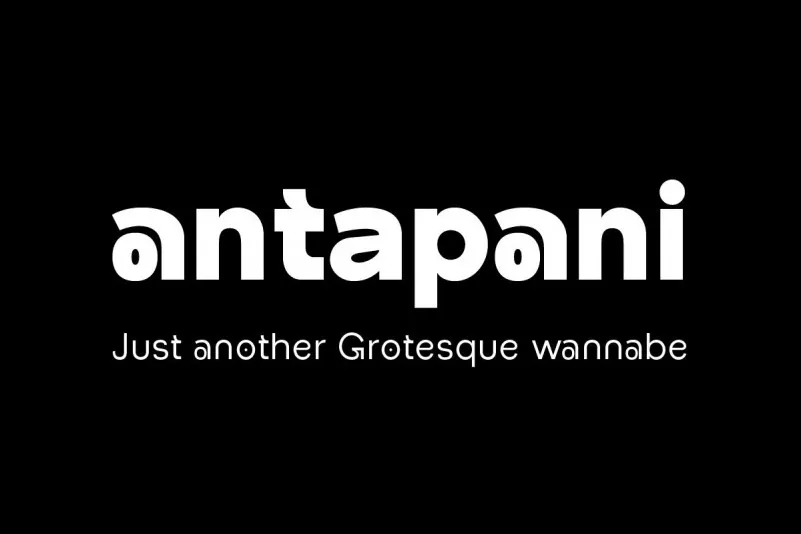
A Befonts está feliz por apresentar uma nova família de fontes sépia moderna. Esta é uma fonte de estilo grotesco que oferece uma forte característica, alta contração e legibilidade, tornando-a confortável para a leitura. Antapani Font foi projetada por Abdurrahman Hanif e compartilhada pela Monocotype Foundry. É um estilo Grotesk que incorpora alguns detalhes estilísticos às letras. Foi projetado não apenas para ser legível, mas também funcional como texto exibição. Com 9 pesos a partir de Reta até Extra Bold, você pode escolher qual é mais adequado. A fonte foi projetada com os recursos OpenType em mente. Cada peso inclui suporte linguístico estendido (+ Cílirico), frações, linhas tabulares, sinais e ligações. Perfeita para design gráfico e uso exibição. Ela se adequaria facilmente tanto para web, sinalização quanto para corporativo ou design editorial.